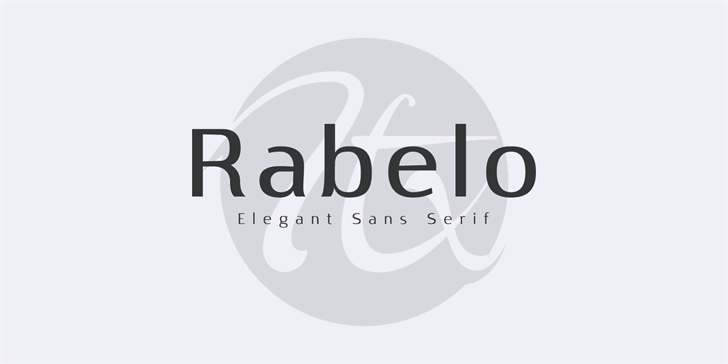
Rabelo Font
A Rabelo é uma fonte do tipo sans serif que oferece seis variações diferentes, desde fina até pesada. Esta família de tipos foi projetada por Hamilton e inclui a variante Regular que está disponível gratuitamente para uso. Com um design limpo e moderno, a Rabelo se destaca por sua simplicidade gráfica, sendo perfeita para textos legíveis em sites, blogs e aplicativos digitais. As variações da fonte permitem que você personalize seu design, criando uma variedade de estilos sem comprometer o equilíbrio visual essencial do tipo. Para quem busca um estilo minimalista e elegante para seus projetos digitais, a Rabelo é uma escolha ótima.